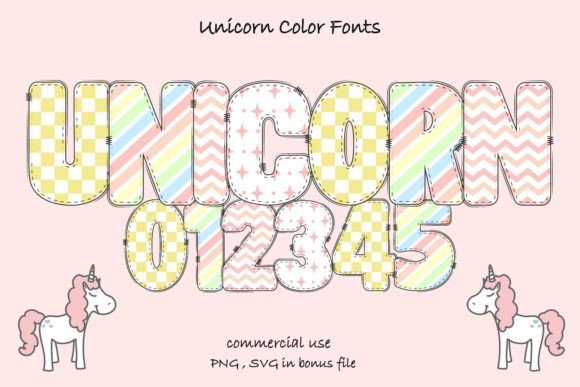
Unicorn
Trouver les bons éléments de conception peut être un défi, mais Unicorn propose une collection exceptionnelle qui rehausse instantanément votre travail.
Que vous créiez des produits POD (impression à la demande), des invitations de mariage ou des visuels pour les réseaux sociaux, Unicorn est un choix idéal.